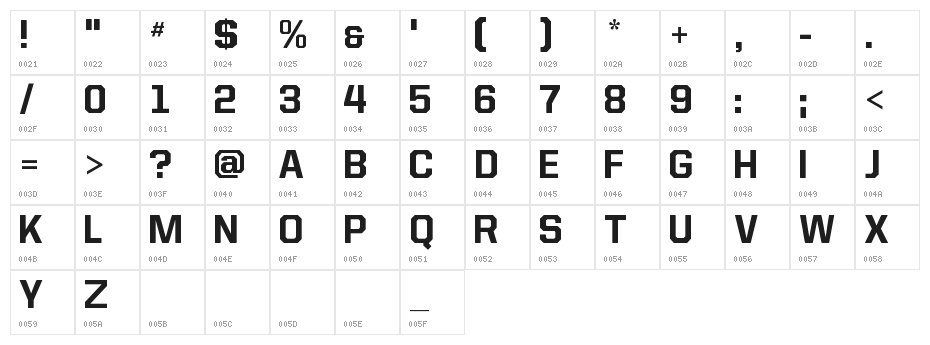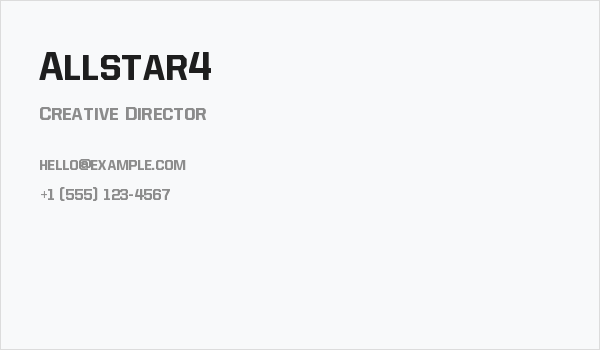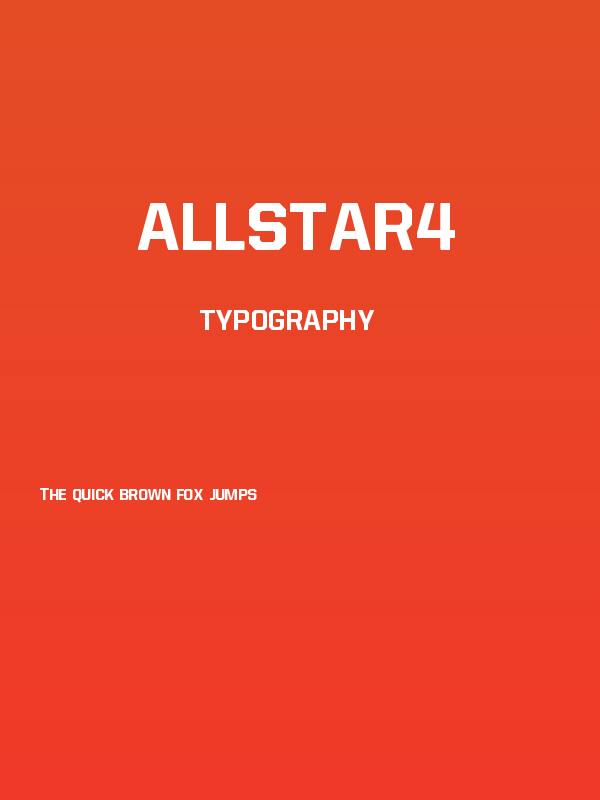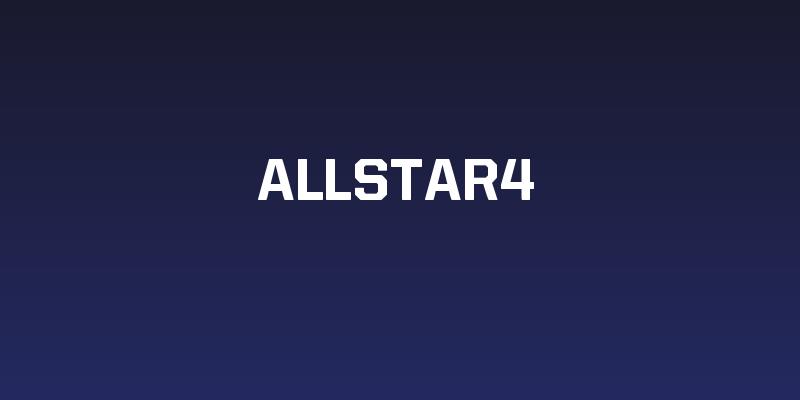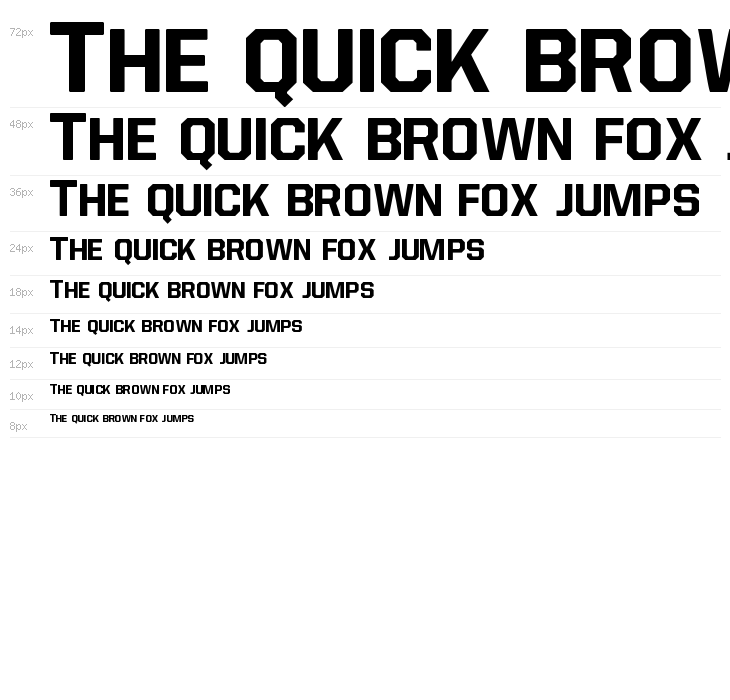
Allstar4 Font
✎ Old fashioned
| Proyectos propuestos | Ideal for sports branding, industrial design, posters, and headlines that require a strong visual impact. |